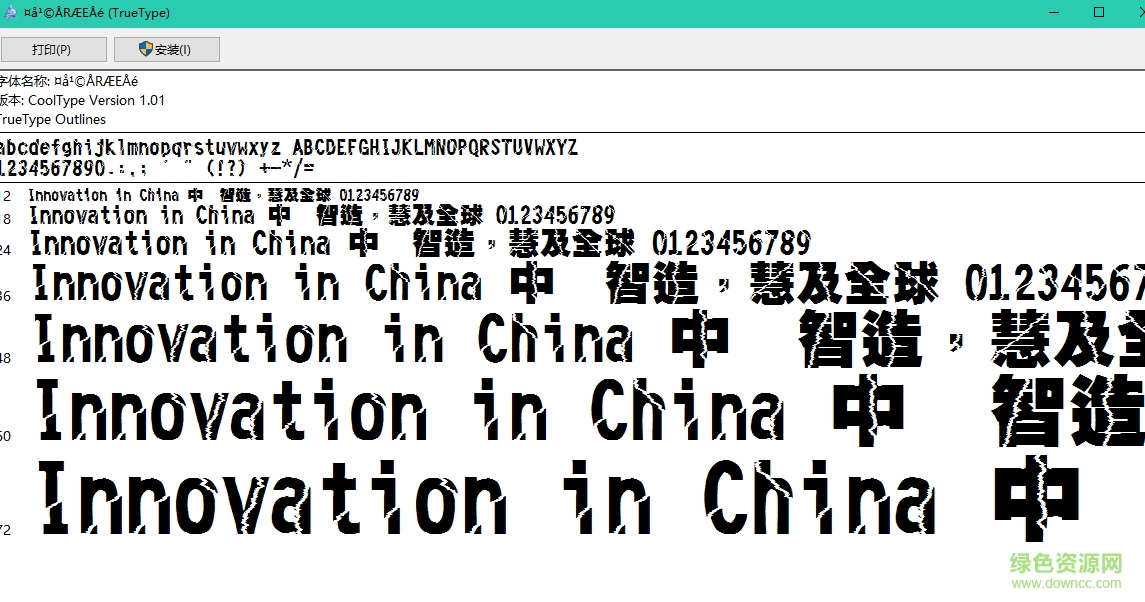
文鼎霹靂繁體字體
文鼎霹靂繁體是一款個(gè)性十足的字體,不同于一般的文鼎字體,該字形非常漂亮,正直剛毅,狂野味道,不拘一格。有興趣的快來(lái)綠色資源網(wǎng)下載體驗(yàn)吧!
文鼎霹靂繁體字體簡(jiǎn)介
文鼎霹靂繁體是一款風(fēng)格非常鮮明的中文字體,端正、橫豎整齊,字體又有一點(diǎn)分叉的小心機(jī)設(shè)計(jì),非常時(shí)尚。
文鼎霹靂體字體